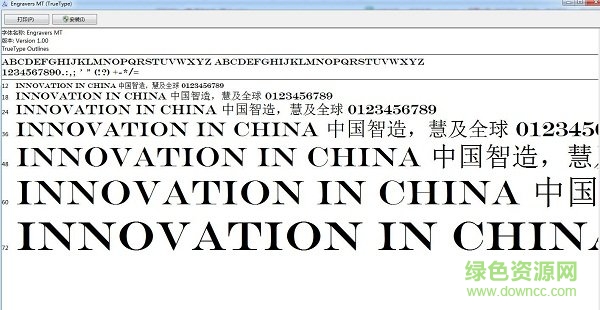
engravers mt字體是一款橫細(xì)豎粗的時(shí)尚字體,字體的粗細(xì)對(duì)比強(qiáng)烈,筆鋒突出,弧線過(guò)渡平穩(wěn),富有現(xiàn)代氣息,適用于女性化妝品廣告、娛樂(lè)海報(bào)、雜志等領(lǐng)域,有需要者歡迎免費(fèi)下載!